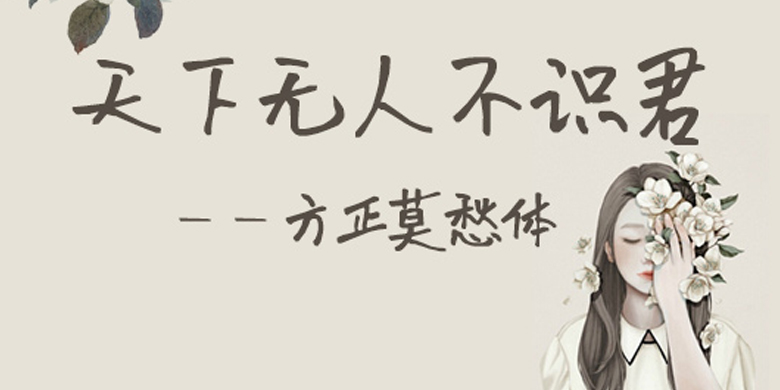
方正手迹-莫愁楷书
方正手迹-莫愁楷书,这款字体结构工整、笔画清晰,兼顾美观与易读性,适用于标题、正文、海报、包装、LOGO 等多种场景。字形优雅稳定,风格百搭耐看,适配日常排版与创意设计,让文字呈现更舒适、更具质感。方正手迹-莫愁楷书一笔一画,皆是细节,以均衡的比例、流畅的线条打造舒适视觉体验,字形端正大气,风格简约现代。无论是商业设计、品牌宣传还是日常排版,都能轻松驾驭,让文字更有格调与力量。方正手迹-莫愁楷书字体下载。
字体品牌: 方正手迹 设计师:方正手迹 字体分类:楷书、创意书写 字体属性:精品字 字符集:大陆简体(GB2312-80) 发布时间: 2020
这款字体行笔成熟老到,书法功底扎实,虽锋藏不露,但掩饰不住一颗炙热跳动的气质。适用于文艺类的书刊、品牌广告和产品包装设计,以及社交网络的个性化用字。